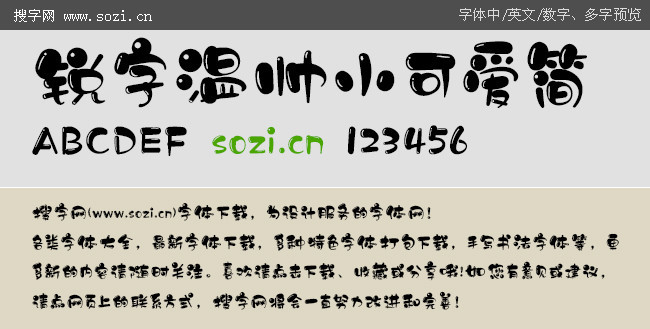
銳字溫帥小可愛簡
搜字網提供一款銳字溫帥小可愛簡中文字體下載,銳字溫帥小可愛簡在可愛體的基礎上添加了高光,更加有立體感。字形溫潤飽滿、親切乖巧,筆畫不拘一格、粗細對比協調、簡化變形有新意且不失識別性,營造了一種輕松歡快、充滿趣味性的氛圍;非常適合兒童海報,包裝設計,網頁設計等設計使用。【本字體供個人非商業免費使用,如需商用請聯系作者授權】